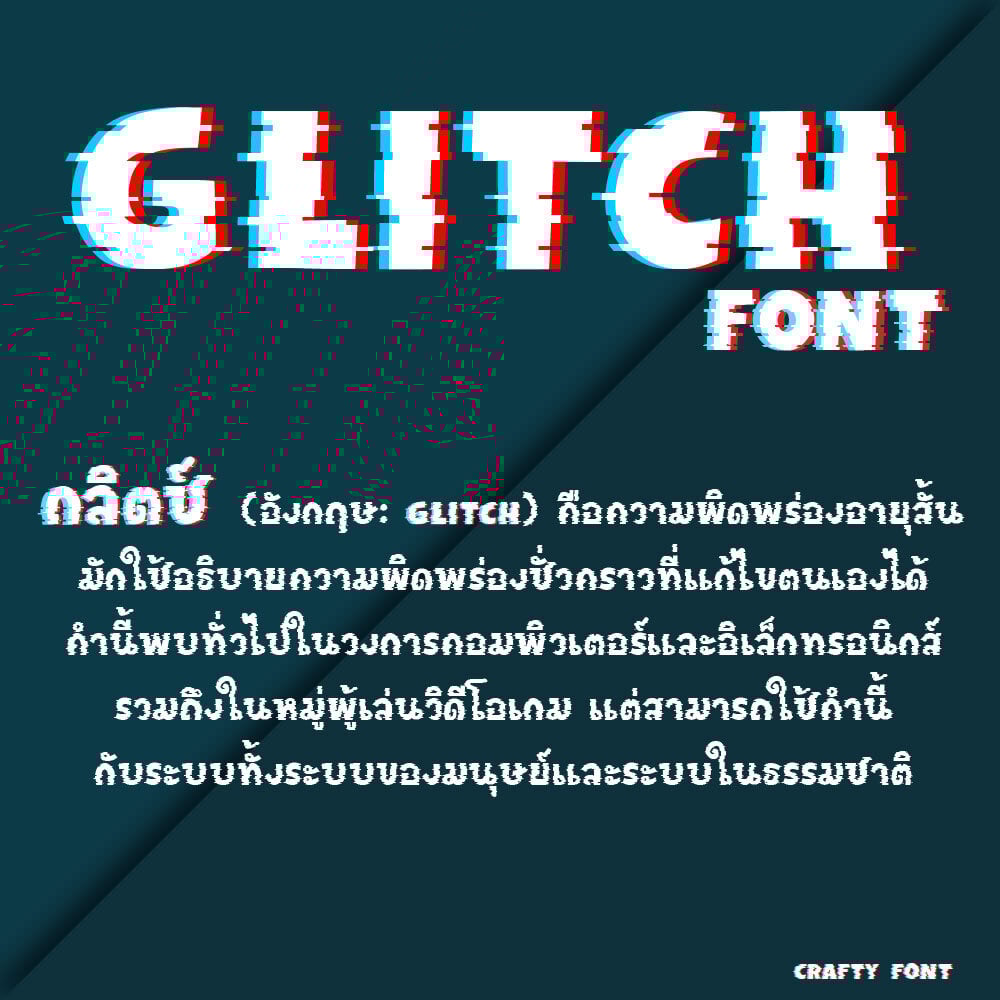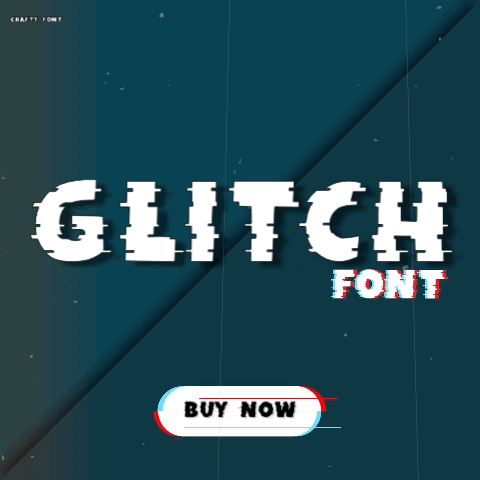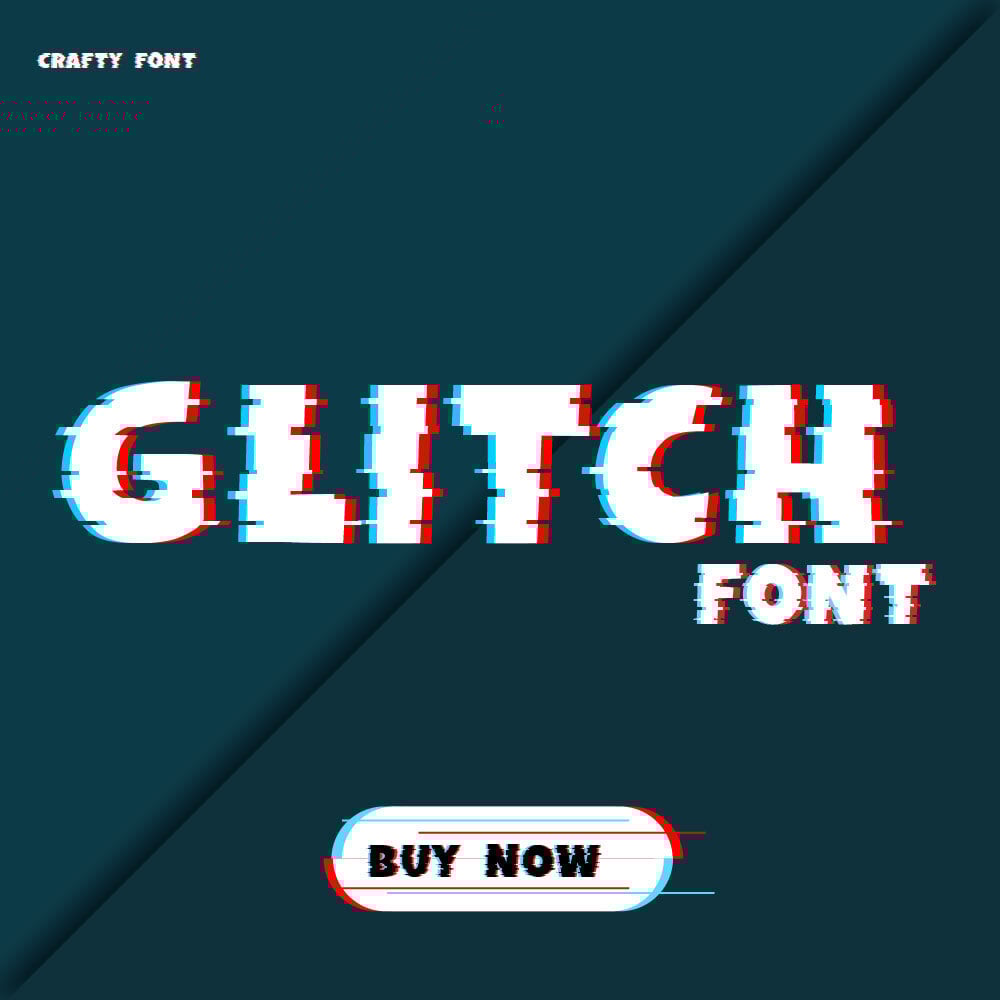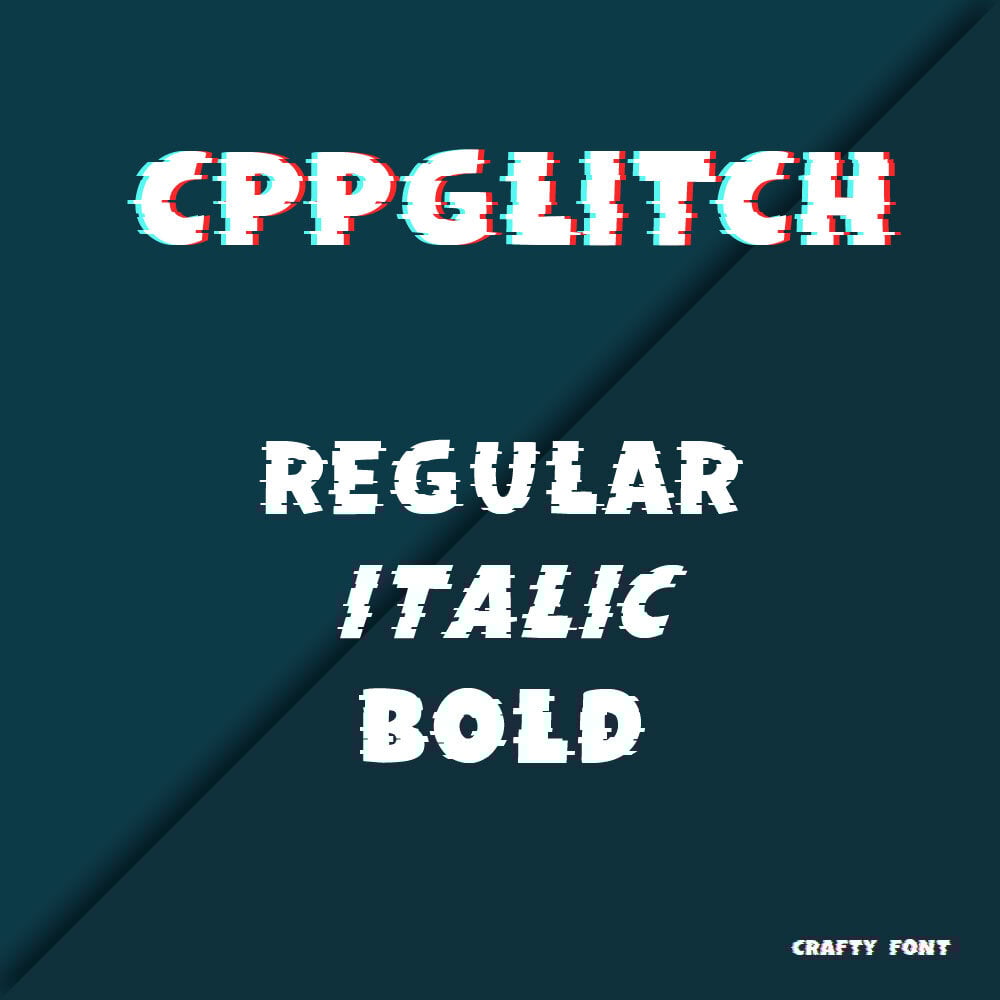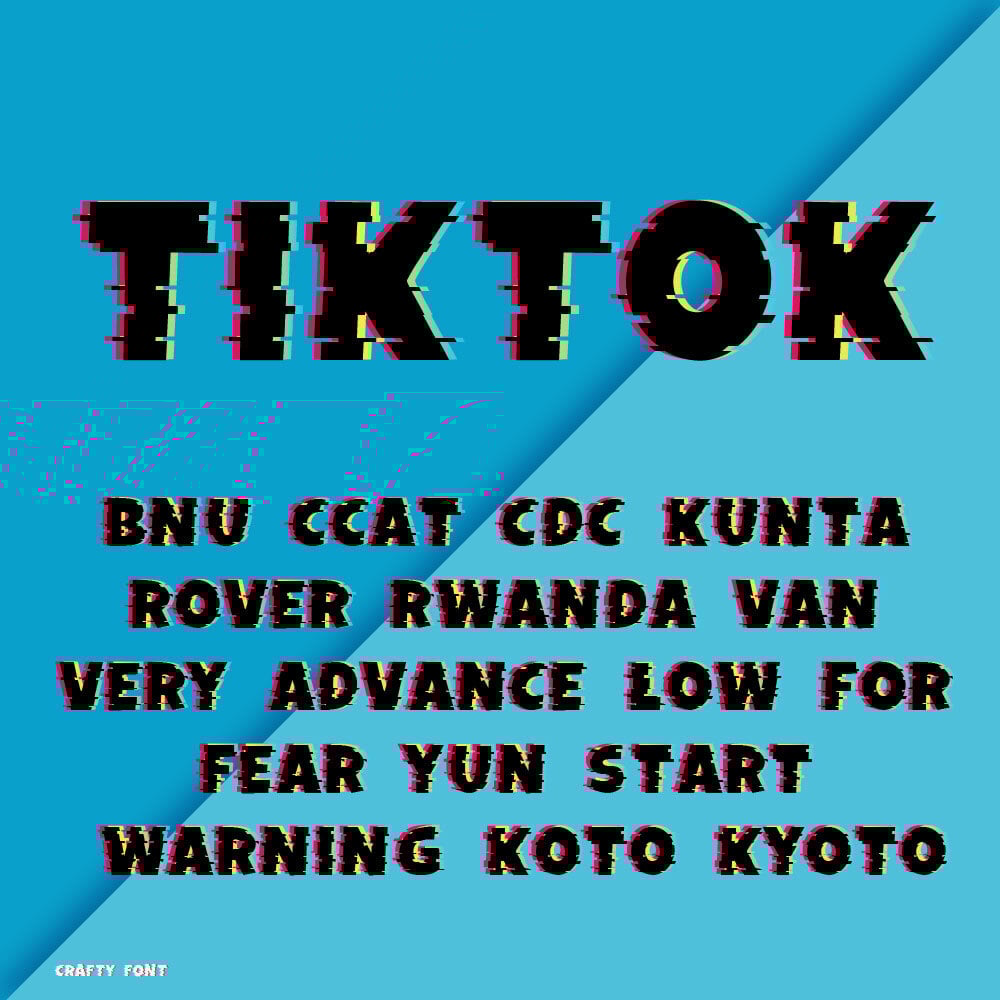
CPP glitch font (ซีพีพี กลิตช์ฟอนต์)
กลิตช์ (อังกฤษ: glitch) คือความผิดพร่องอายุสั้นมักใช้อธิบายความผิดพร่องชั่วคราวในวงการคอมพิวเตอร์และอิเล็กทรอนิกส์
แพนออกแบบฟอนต์ซีพีพีกลิตช์ เพราะเป็นคนชอบเอฟเฟกต์กลิตช์มากๆ เวลาทำงานวิดีโอถ้าคิดอะไรไม่ออก แล้วต้องใส่เอฟเฟกต์ในข้อความ แน่นอนว่าเอฟเฟกต์กลิตช์จะเป็น 1ตัวเลือกที่คิดถึงเสมอ ตัวอักษรก็ออกแบบให้มีเส้นๆ ออกมาเหมือนตัวอักษรตัวนั้นมันช็อตจริงๆ
พิมพ์ได้ทั้งภาษาไทยและภาษาอังกฤษ ตัวเลขสัญลักษณ์บวกลบคูณหารมีครบค่า หวังว่าทุกคนจะชอบนะคะ ❤️